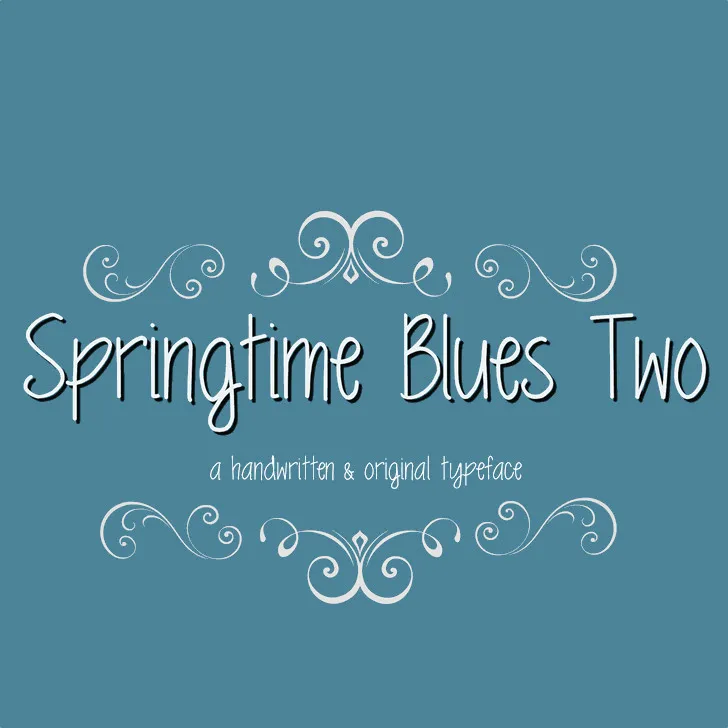
MRF Springtime Blues Two Font – Download Grátis
Aqui está uma versão descritiva para a página de download da font “MRF Springtime Blues Two Font” na categoria de Fonts Pintadas: A font MRF Springtime Blues Two é um toque de escrita livre e entusiasmado que combina elementos suaves com um ar descontraído. Desenvolvida pelo designer Hamilton, essa elegante fonte hand-written oferece uma maneira única para ilustrar textos em qualquer projeto pessoal ou comercial. Se você está procurando por uma fonte que se destaca sem precisar de grandes esforços, certamente a MRF Springtime Blues Two é a escolha perfeita. Com seu estilo natural e fresco, esta font pode ser a solução ideal para aqueles que buscam um pouco mais de personalidade em seus projetos. Seja para criar cartazes alegres ou simplesmente dar uma pitada de originalidade à sua página web, MRF Springtime Blues Two é um atalho direto para o coração do design gráfico com um toque suave e vibrante. Esta font não apenas adiciona um charme único ao seu projeto pessoal ou a sua marca comercial, mas também dá uma personalidade extra que pode ser usada em qualquer aplicação onde você esteja desenhando texto. Perfect para criar mensagens memoráveis e atingir o coração do seu público-alvo.